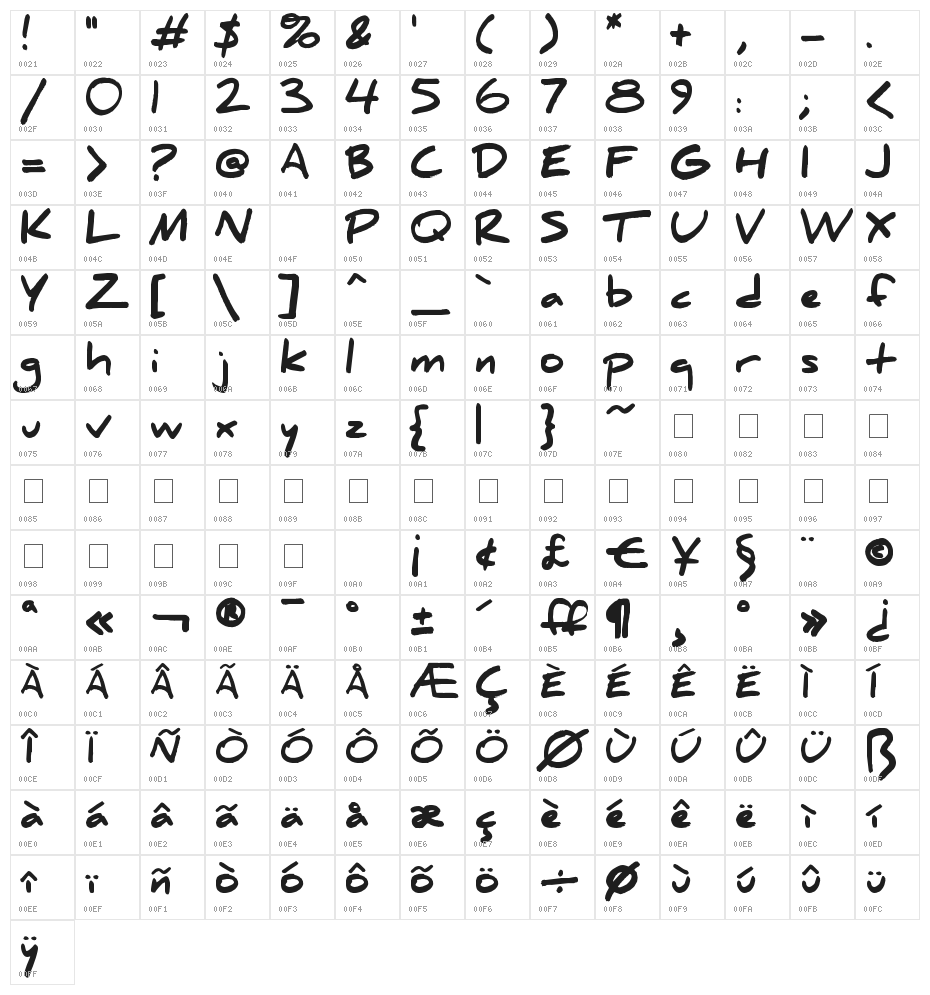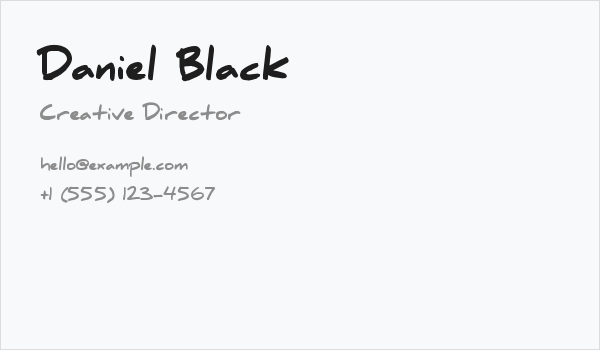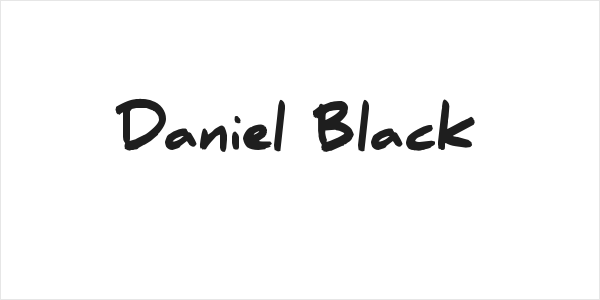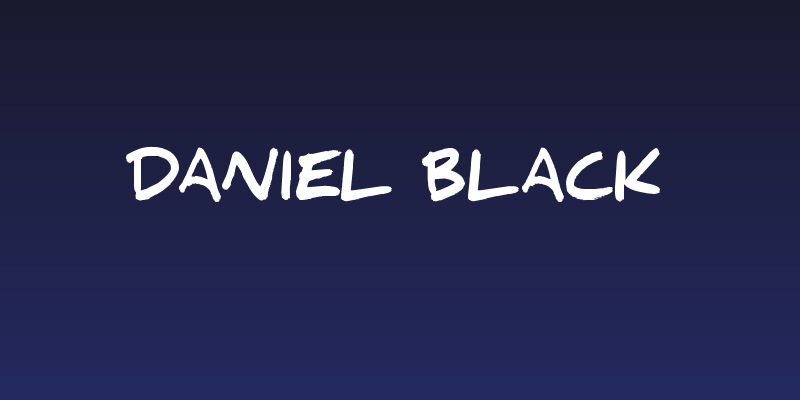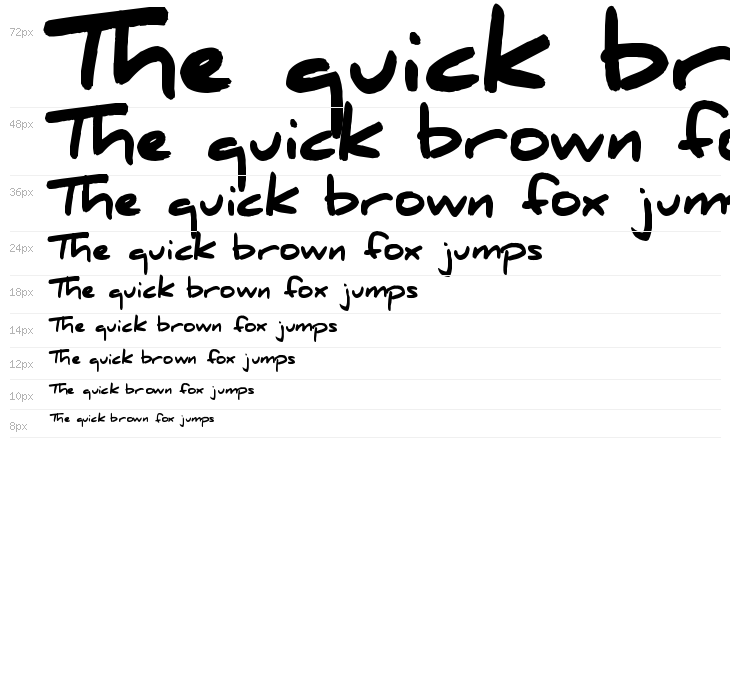
Daniel Black Font
| Stile generale | Casual, Playful |
| Caso d'uso | Headlines, Logos, Informal Text |
| Progetti proposti | Ideal for greeting cards, personal branding, informal invitations, and creative projects that seek a personal touch. |